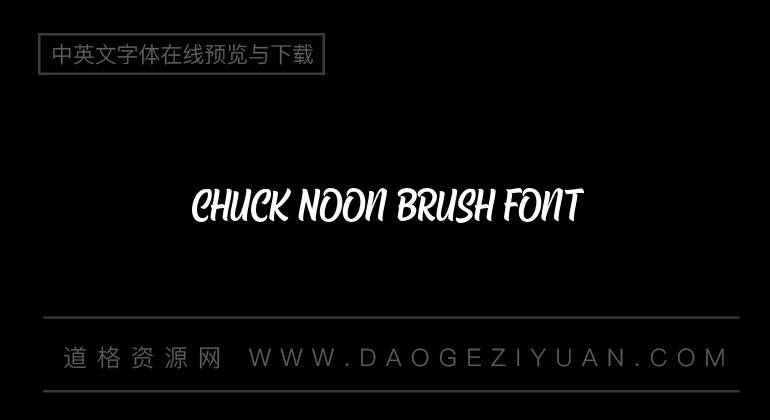
Chuck Noon Brush是一种手写风格的字体,具有粗糙,自然和原始的外观。它具有高质量的笔画纹理和斜率,使其看起来像是由一支粗笔创造的。这种字体通常用于设计海报,书籍封面,标志,品牌,广告等方面。它的独特风格和个性化使其成为设计师和艺术家的流行选择。Chuck Noon Brush字体支持多种语言,可以在Windows和Mac OS上使用,并提供一些额外的字符和标点符号,以增强其视觉效果。内容介绍
Chuck Noon Brush Font是一款非常不错的手写艺术字体,具有很好的视觉感,适合于文化类的宣传设计、商业类品牌的广告和产品包装设计以及个性化文字排版等较多场景。